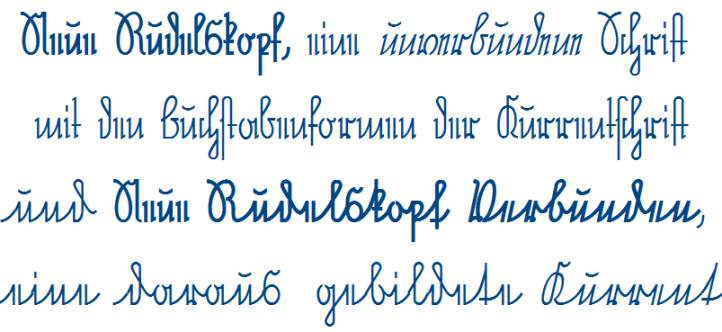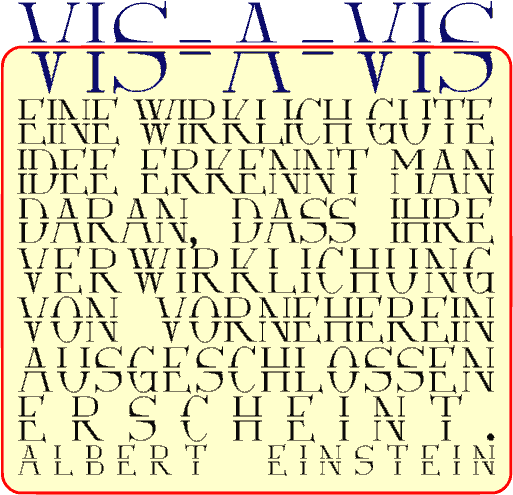
Experimentelle Typografie
Ich möchte hier mehr über die Geschichte und Entwicklung der "Experimentellen Typografie" herausfinden, da man per Google-Suche dazu nicht viel findet. Auch nicht ganz klar ist mir, welche Bereiche der Typografie denn jetzt alle unter den Begriff "experimentell" fallen.
Hast Du denn überhaupt schon mal abseits des Internets recherchiert? Es gibt zur Typografie jede Menge guter Bücher, die Dir weiterhelfen können. Die Suche lohnt sich …  ;-)
Ganz grundsätzlich zur experimentellen Typografie: Experimentell ist sie dann, wenn sie über die gelernten, etablierten Anwendungen von Schrift, also das Setzen von Texten zum Zwecke des Gelesenwerdens, hinausgeht und versucht, zusätzliche Inhalte abseits des reinen Wortlautes durch die Art der Gestaltung mit Schrift zu transportieren. Informiere Dich doch mal über Jan Tschichold, der sicher einer der ersten und bedeutendsten experimentellen Schriftkünstler und einer der Hauptakteure in Sachen »Neue Typographie« war. Aber recherchiere auch zu David Carson und Neville Brody, um nur mal einige wenige der Gestalter zu nennen, die sich experimentell mit Schrift befasst haben. Viel Erfolg und Spaß dabei!  :-)
Also ja, wenn es denn ein Buch sein darf: Es gibt unter dem Titel »Typografie kann unter Umständen Kunst sein« drei Bände zur Entwicklung der modernen, sozusagen experimentellen Typografie im frühen zwanzigsten Jahrhundert, hier gibt zu es einem Band mehr Infos: http://www.artbookcologne.com/books/design/art-06908.html (kann man auch bei amazon erwerben).
Ansonsten ist, wie Kathrin schon sagte, Jan Tschichold ein guter Ausgangspunkt auch zur Bestimmung, worin sich die experimentelle Typografie von »allgemein« Typografie unterscheidet, weil er von modernen Anfängen sich zu Regeln klassischer Typografie zurückwandte.
Wolfgang Weingart, Hans-Rudolf Lutz als neuere Vertreter fallen mir noch ein. Ach, und noch die grande dame der New Wave Typografie, April Greiman ;-)
Vieles, was mal "experimentelle Typografie" war, wirkt heute nicht mehr besonders experimentell. Andererseits zeichnet sich experimentelles u.a. auch dadurch aus, dass es "neu" oder zumindest ungewöhnlich wirkt ... und deshalb nun eben nicht in allen Mainstreamkanälen auf Anhieb zu finden ist. Und in gewisser Weise ist ja fast jeder Grafiker beim Versuch etwas Auffallendes und/oder Ungewöhnliches zu schaffen ein Experimentator. Im Grunde waren auch Gutenberg, Manutius, Garamond etc. Experimentatoren. Schon deshalb solltest Du das Suchgebiet etwas eingrenzen, sonst findest Du alles und nichts. Es gab und gibt neben all den genannten noch jede Menge andere typografischer Experimentatoren: die Futuristen in Italien, die Surrealisten in Frankreich und der Schweiz, Typografen in Ungarn, der damaligen CSR und Rußland vor dem zweiten Weltkrieg, holländische, belgische, französische und sonstige Pressendrucker, die "konkrete Poesie" in Europa und Amerika seit den frühen 60ern, etliche "Samisdat"-Leute im Ostblock, autonome und sonstige radikale Pressen und Plakatmacher, etliche angesehene Kleinverlage in Europa haben mit Buchtypo und Buchkunst exprimentiert bis hin zu den sogenannten Malerbüchern, "richtungsweisende" und/oder auch nur kurzlebig "hippe" Grafiker, Typografen, Grafikagenturen von Lucian Bernhard über diverse Amerikaner, Schweizer, Holländer und viele andere bis hin zu diversen Fontshöpfern - und das ist nur ein Teil derer, die mit Typo experimentiert haben ... Es gibt noch viel mehr, man kann sich ein Leben lang damit beschäftigen und findet immer wieder diesbezüglich Neues und bisher unbekanntes Altes.
Typografische Experimente gibt es seit der Erfindung des Buchdruckes. Es wäre in deinem eigenen Interesse sinnvoll, sich auf eine bestimmte Zeit zu beschränken. Ferner spielt für die Recherche das Medium (Buch, Plakat, Akzidenzen etc.) eine nicht zu unterschätzende Rolle.
> Geschichte und Entwicklung der "Experimentellen Typografie"
Das gibt es nicht.
Was ist »die experimentelle Typographie«?!
Tja, die Übergänge sind fließend. Wenn man von experimenteller Typografie spricht, dann sollte es ja wiederum auch experimentelle Typografen geben. Bei Protagonisten wie Raoul Hausmann und Theo van Doesburg überhaupt von Typografen zu sprechen, fällt mir ziemlich schwer. Bei Tschichold, der unbestritten einer der bedeutendsten Typografen des 20. Jahrhunderts war, stand das Experiment zu keiner Zeit im Vordergrund seines typografischen Schaffens – weder in den 1920er Jahren noch später. Also, wo fängt man an, wo hört man auf?
Wenn man von experimenteller Typografie spricht, dann sollte es ja wiederum auch experimentelle Typografen geben.
Würde ich nicht unbedingt sagen. Auch ein einzelne Übungsaufgabe von Studenten an der Uni kann experimentelle Typografie sein. Und was experimentell heißt, sollte ja eigentlich auch klar sein. Duden sagt:
(Kunst, Literatur, Musik) (versuchsweise) mit besonderen, neuartigen, ungewöhnlichen, fremd wirkenden künstlerischen Mitteln frei gestaltet, komponiert.
Sowas gab es zu allen Zeiten und dass etwas im Kontext und der Zeit gerade besonders/neuartig/ungewöhnlich/fremd – oder eben kurz experimentell – war, lässt sich auch recht klar herausarbeiten.
Aber letztlich ist doch die Frage, warum Typebird überhaupt fragt. Wie bist du über diesen Begriff gestolpert und warum interessiert er dich? Oder war es gar wieder eine dieser typischen Aufgaben aus der Lehre, wo ein Dozent den Studenten irgendwelche Begriffe zum Erforschen aufgibt? Letzteres finde ich immer etwas schwierig, weil der Dozent wohl recht klare Vorstellungen hat, was es da zu erforschen gibt, aber der Begriff dies ohne jeglichen Kontext womöglich gar nicht hergibt. Solche Fragen hatten wir ja schon vielfach hier.
@typebird – Von diesem Einwand würde ich mich nicht entmutigen, sondern anstacheln lassen – mit der Möglichkeit im Blick, daß es experimentelle Typografie nicht als Gattung gibt. Offenbar ist es zu kurz gegriffen, unter dem Begriff Experimentelle Typografie die Neue Typografie und Dada zu verstehen. Für mich und einige andere war das offenbar die erste Assoziation. Ob die nun unberechtigt ist? Wikipedia bietet diese Definition auch, allerdings unbelegt. Vielleicht ist diese Denkrichtung falsch. Du müßtest eine Definition finden, die belastbarer ist als eine Behauptung oder ein Einfall. Das wäre dann wirklich nur »Schlagworthascherei«. Kathrins Definition für Experimentelle Typografie erscheint mir nicht geeignet: »Experimentell ist sie dann, wenn sie über die gelernten, etablierten Anwendungen von Schrift, also das Setzen von Texten zum Zwecke des Gelesenwerdens, hinausgeht und versucht, zusätzliche Inhalte abseits des reinen Wortlautes durch die Art der Gestaltung mit Schrift zu transportieren.« Typografie verdient ihren Namen nicht, wenn sie nur Text darstellt zum Lesen, dazu brauchte man nur einen Bleistift. Typografie ist immer mehr als reine Textwiedergabe. Der Begriff Experiment kommt eher aus der Wissenschaft als aus der Kunst und hat etwas mit Neuerung, Erfindung, Probe und Beweis zu tun. Eine typografische Problemlösung ist in der Regel kein Experiment. Dada ist es im Wortsinne auch nicht, denn was wäre damit bewiesen? Es ist künstlerische oder inszenierte oder auch nur wilde Typografie. Schlagworthascherei ist es wohl wirklich, wenn man nur irgendetwas durcheinanderwirft und das Bild dann experimentell nennt. Das sagt ja gar nichts, worin bestünde das Experiment? Gutenberg hat experimentiert, bis er eine Lösung gefunden hat, dem Gedanken kann ich folgen. Gutenberg hatte viele Probleme zu lösen, auch seinem Blocksatz müssen Experimente vorausgegangen sein, bis er auf die Idee kam, verschieden breite Buchstaben herzustellen. Auch der Dramensatz ist sicherlich Folge eines Experimentes gewesen. Die andere Denkrichtung ginge in Richtung Kunst. Dann wäre exprimentell alles, was dem eigentlichen Ansinnen typografischer Arbeit entgegenstrebt. Mit etwas Boshaftigkeit könnte man das auch abtun als Dekorationstypografie. Also: unternimm Definitionsexperimente!